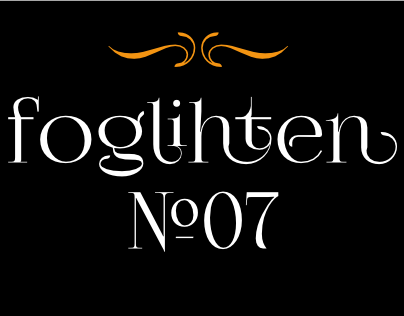
Introduzimos uma família de fonts. Nos introduzemos a Foglihten No07 Font! Desenhada pelo Hamilton, essa serifada fonte de efeito é perfeita para aplicações visuais que exigem um toque moderno e decorativo. Foglihten No07 apresenta ligaturas padrão, conjuntos estilizados, ligaturas decoraivas, formas inicial e terminal. Adicionalmente, a versão calço com formas inicial e final é fornecida como alternativas contextuais padrões. Esta fonte traz um toque de sofisticação às suas criações digitais, dando-lhe flexibilidade para adaptar o design de acordo com seu projeto. Atrai quem procura uma fonte que combine elegância moderna com personalidade. Foglihten No07 é ideal para aplicativos web ou impressos, oferecendo um toque único às suas criações digitais. Essa família de fonts pode dar a sua obra uma cara única e singular, sem comprometer o design profissional. É perfeita para uso em logotipos, títulos e outros elementos visuais que precisam destacar-se na tela ou impressão. Combinada com seus conjuntos estilizados e ligaturas padrões, a Foglihten No07 é uma escolha inteligente para aqueles que buscam um toque de elegância em suas criações digitais.